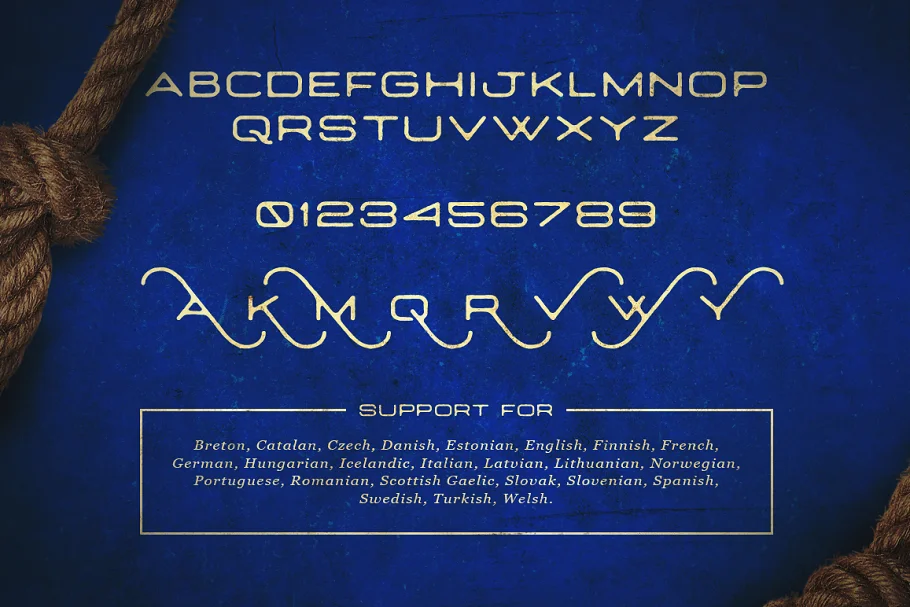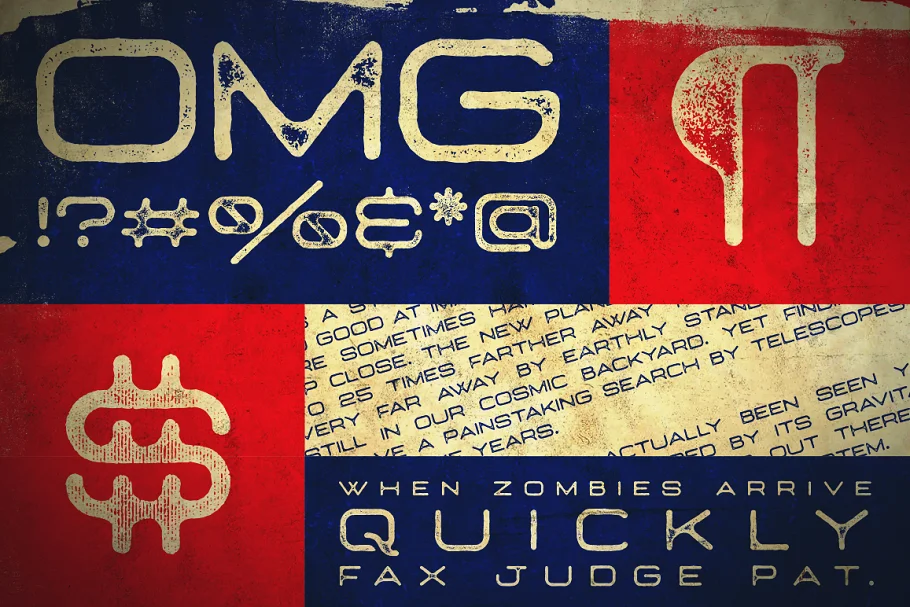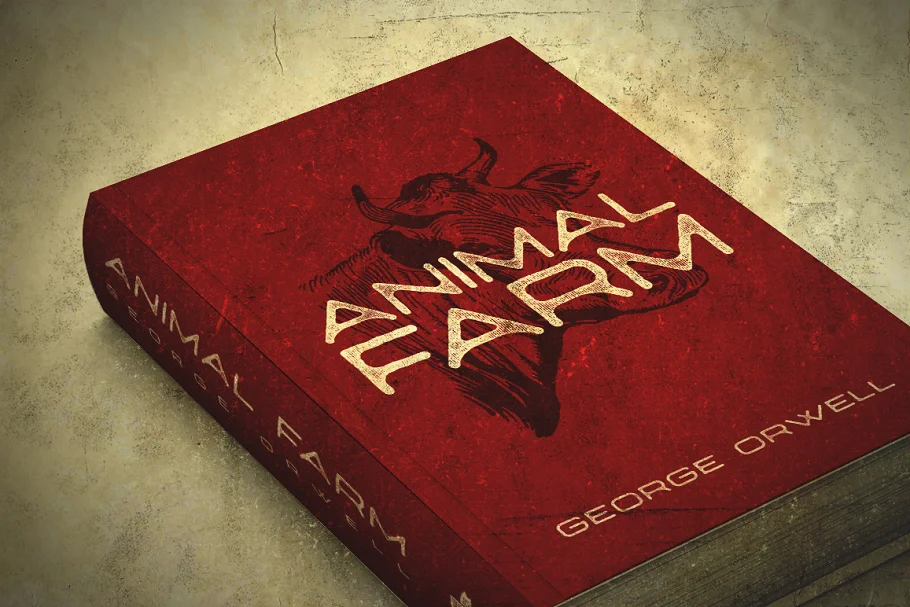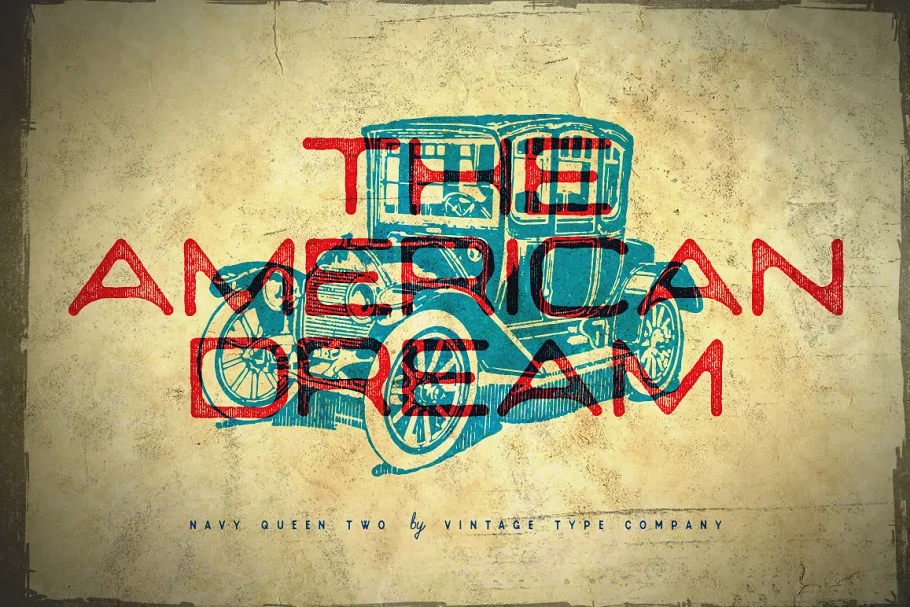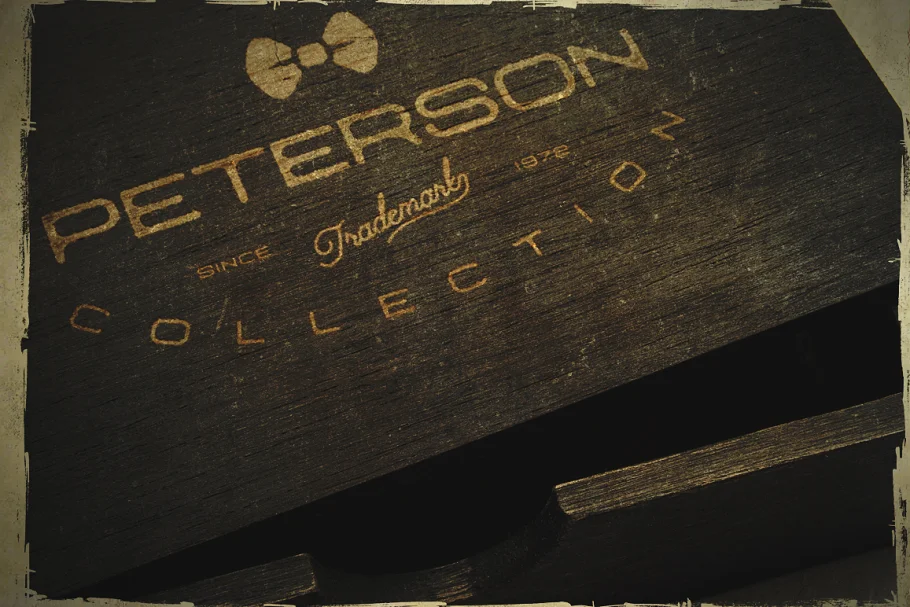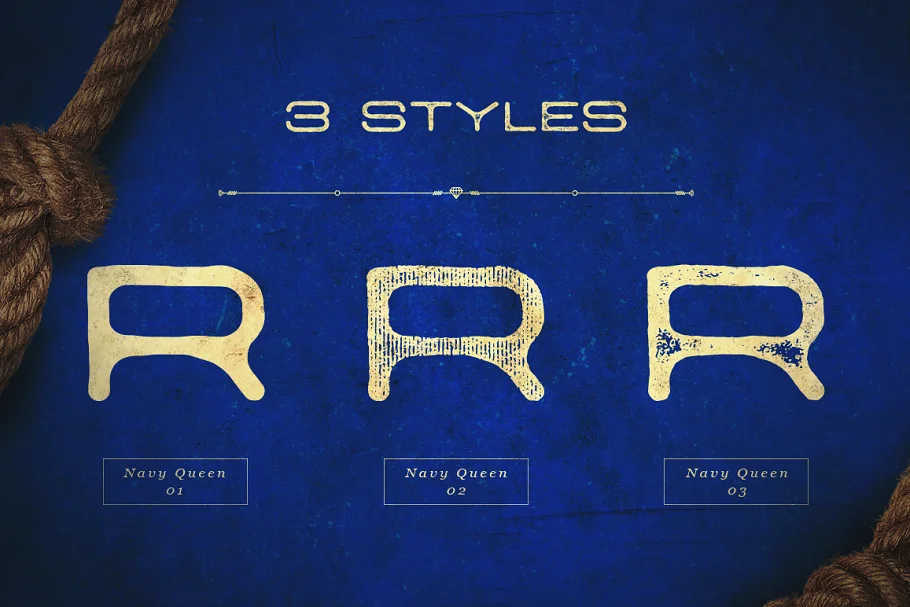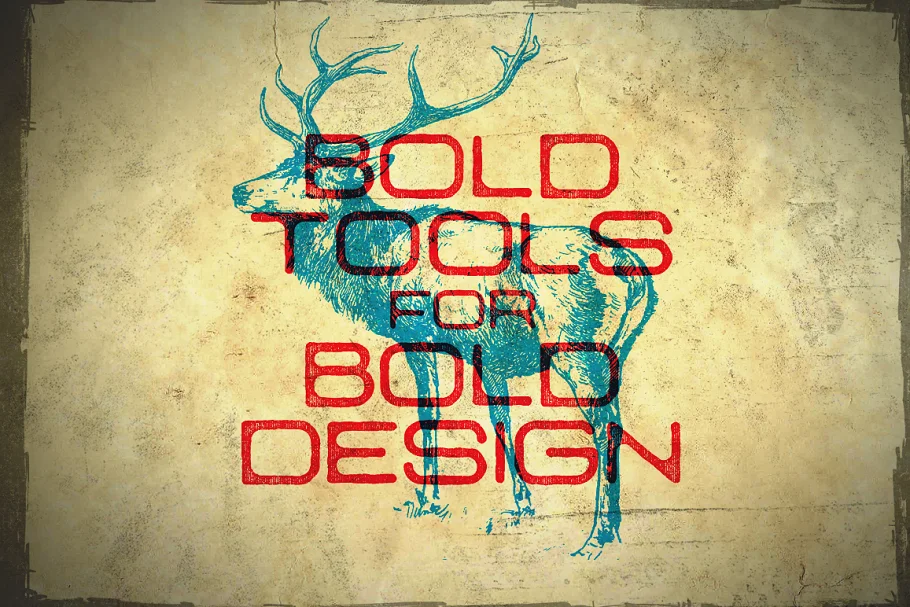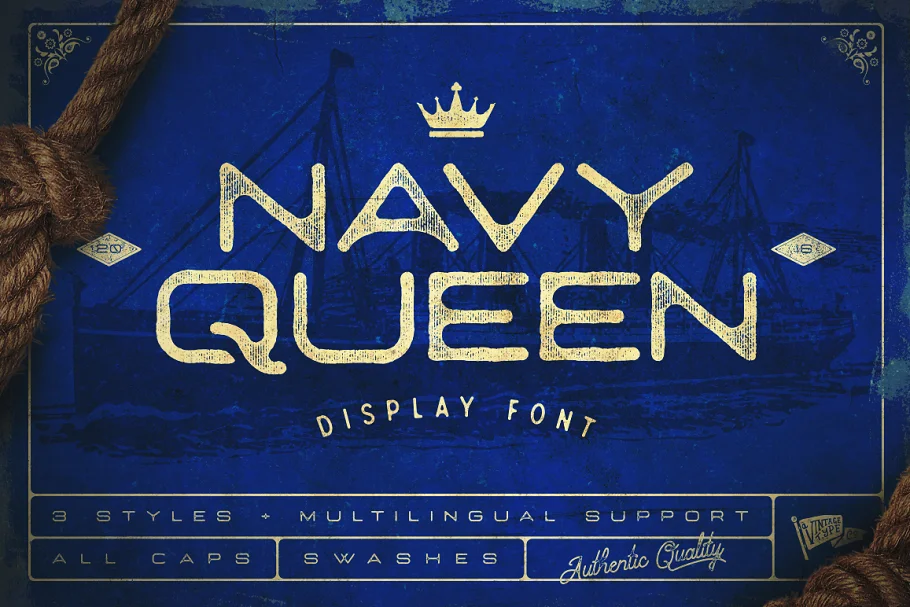
Navy Queen là một phông chữ hiển thị sans serif được mở rộng quá mức, được thiết kế theo hình học để bày tỏ lòng tôn kính đối với thời đại đơn giản hơn. Phông chữ này sẽ hoạt động như một sự bổ sung tuyệt vời cho bất kỳ dự án thiết kế cổ điển nào bao gồm áp phích, logo, biểu tượng, bao bì, v.v.
Navy Queen có phong cách sạch sẽ cũng như hai phong cách đau khổ khác nhau. Nó cũng được trang bị hỗ trợ cho nhiều ngôn ngữ Latin, cũng như các phần thưởng bổ sung.